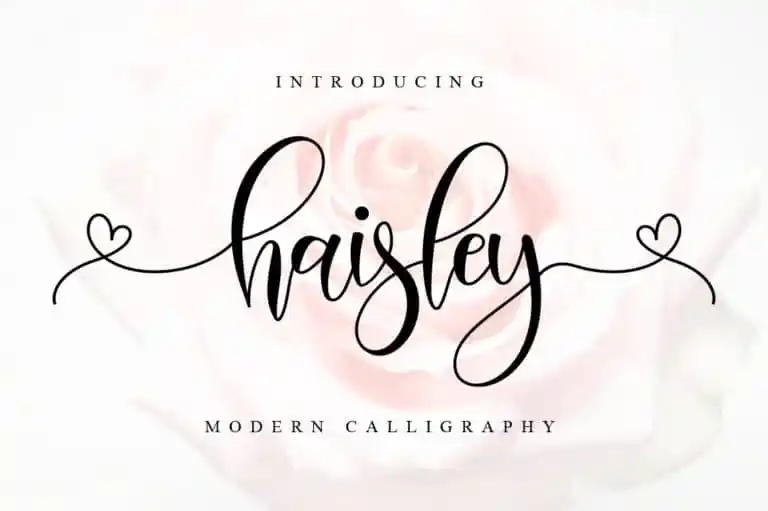
A Haisley Calligraphy Font é uma tipografia moderna e calligráfica criada pela NissaStudio com várias ligações alternativas. Seu estilo sofisticado, elegante e moderno faz dela uma opção ideal para diversas finalidades gráficas, desde identidades corporativas até postagens nas redes sociais, passando por anúncios, estilos de correspondência ou até mesmo desenhos de casamento. Suas linhas sutis e detalhes perfeitos a tornam um recurso versátil que pode se adaptar a muitos projetos visuais. Essa fonte é uma excelente escolha para quem busca um equilíbrio entre elegância e simplicidade em seus trabalhos digitais ou impressos, sem perder o charme do estilo tradicional da calligrafia.